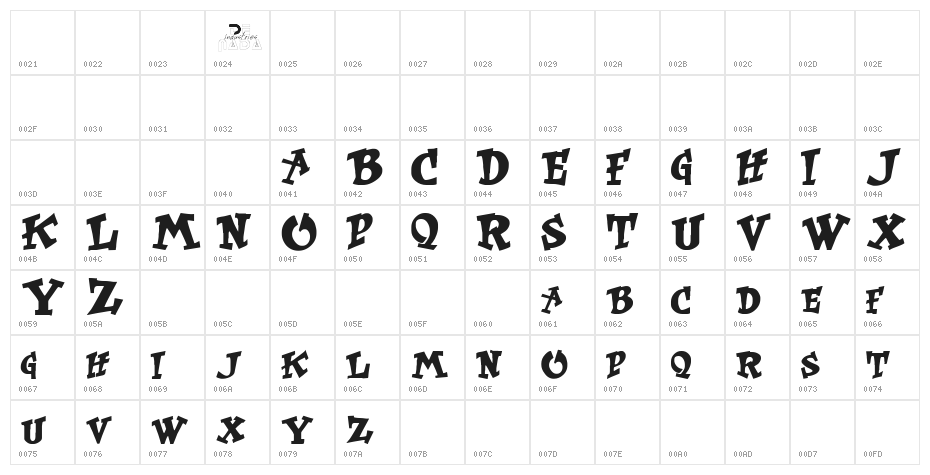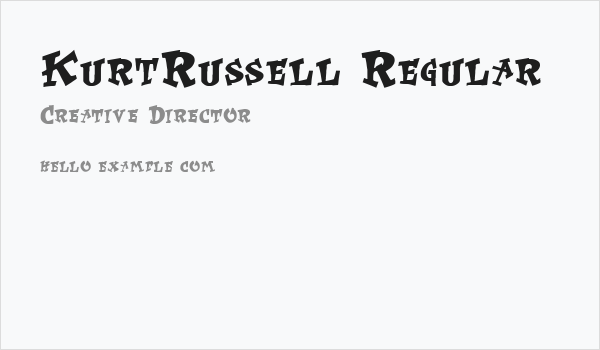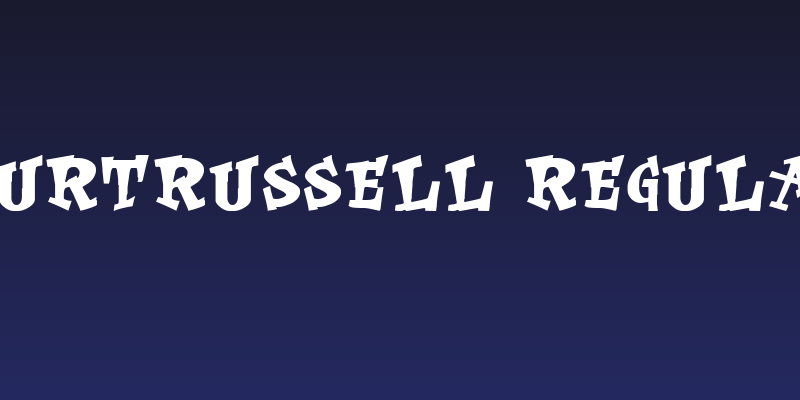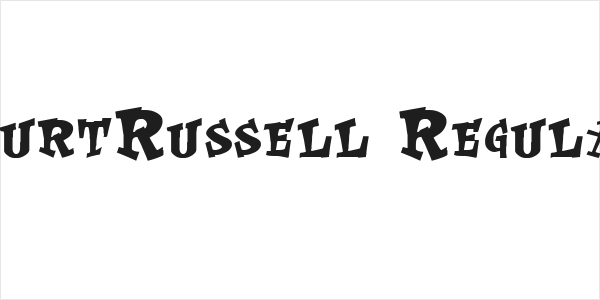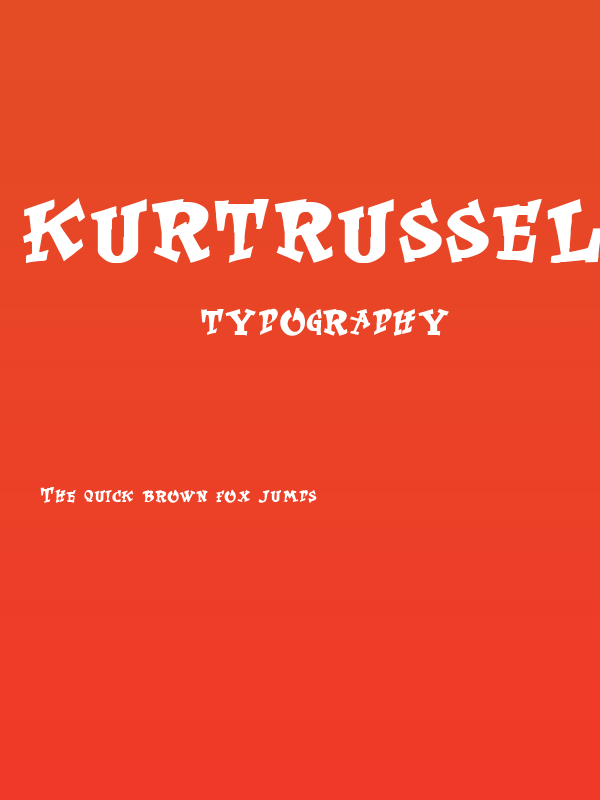
KurtRussell Regular Font
✎ Capitals
Fonts by DeNada Industries - Mike Allard
| Categorie | Capitals |
| Stile generale | Playful, Energetic, Decorative |
| Caso d'uso | Headlines, Posters, Invitations |
| Progetti proposti | Ideal for children's books, posters, party invitations, and any project needing a lively touch. |